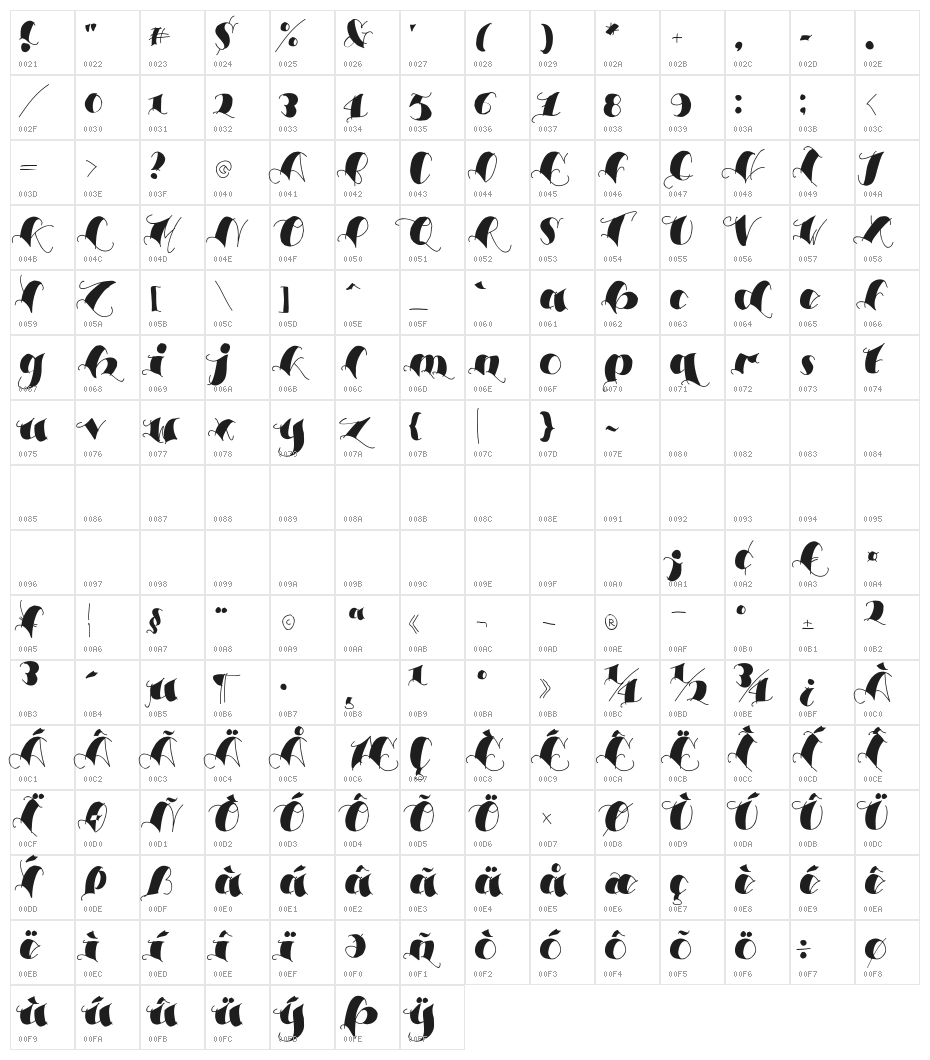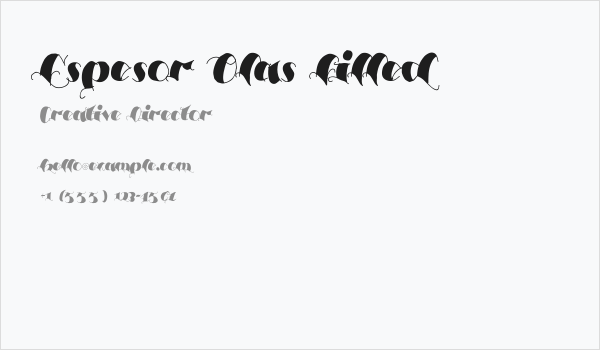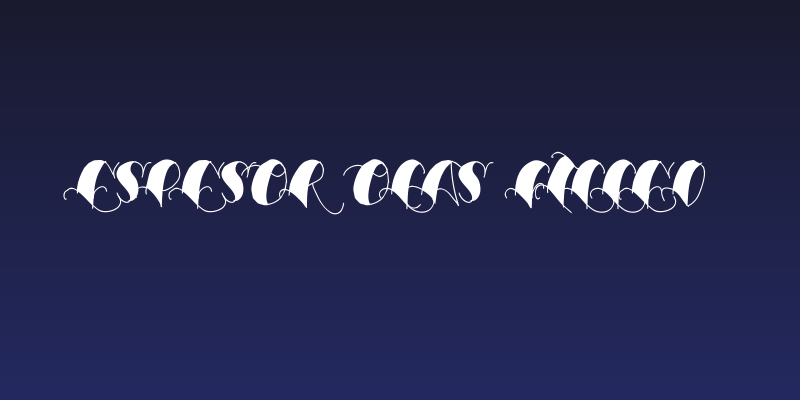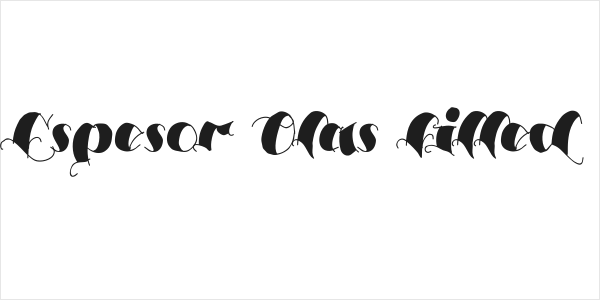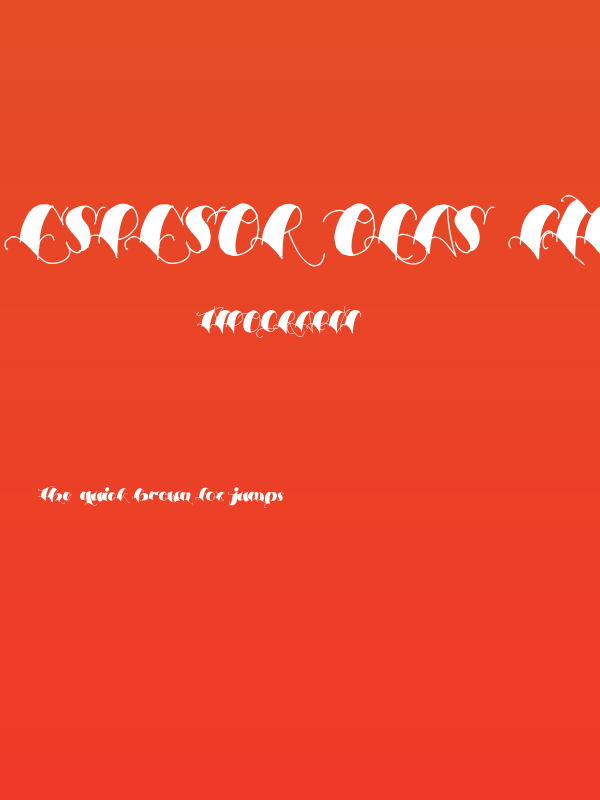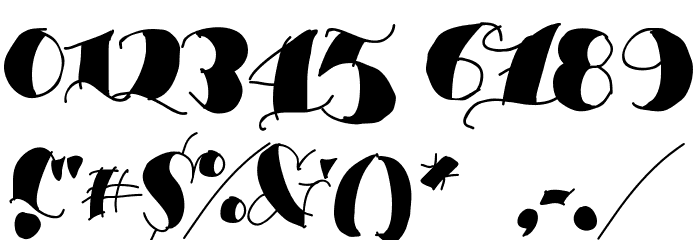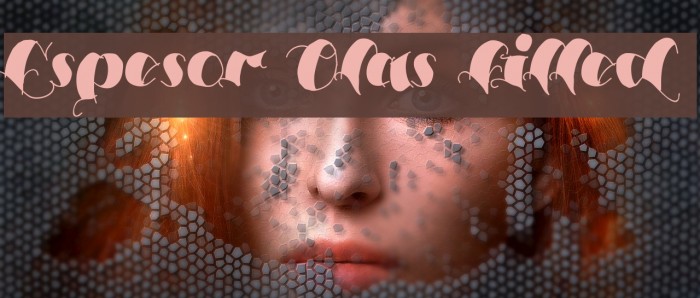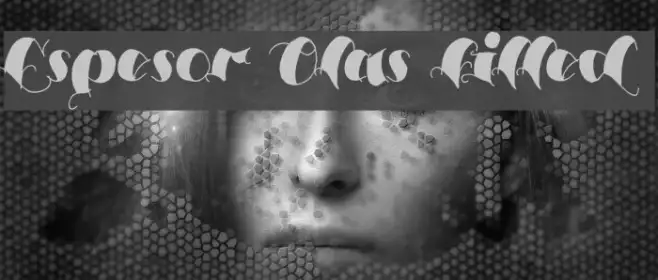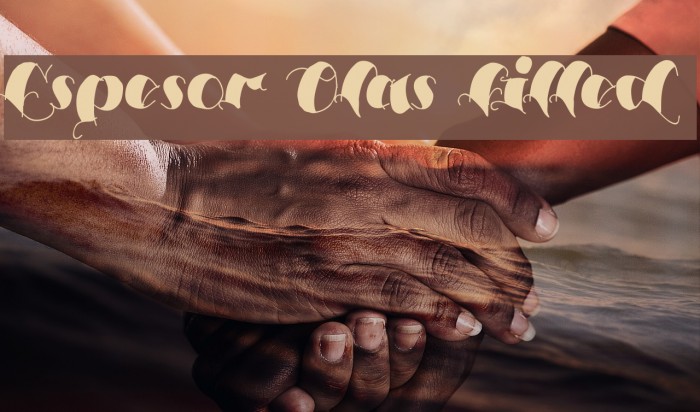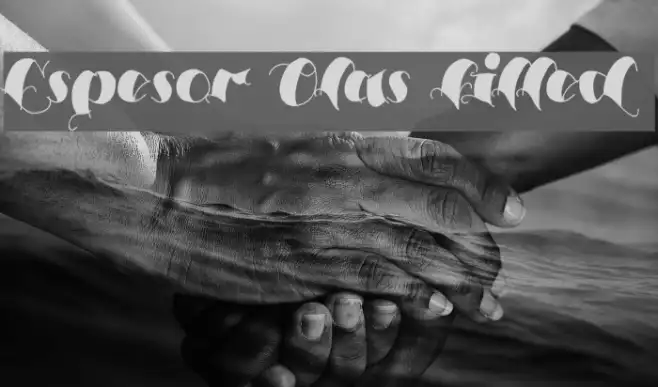
Espesor Olas Filled Font
| Caso d'uso | Logos, Headlines, Invitations |
| Progetti proposti | Ideal for wedding invitations, luxury branding, elegant posters, and artistic projects. |